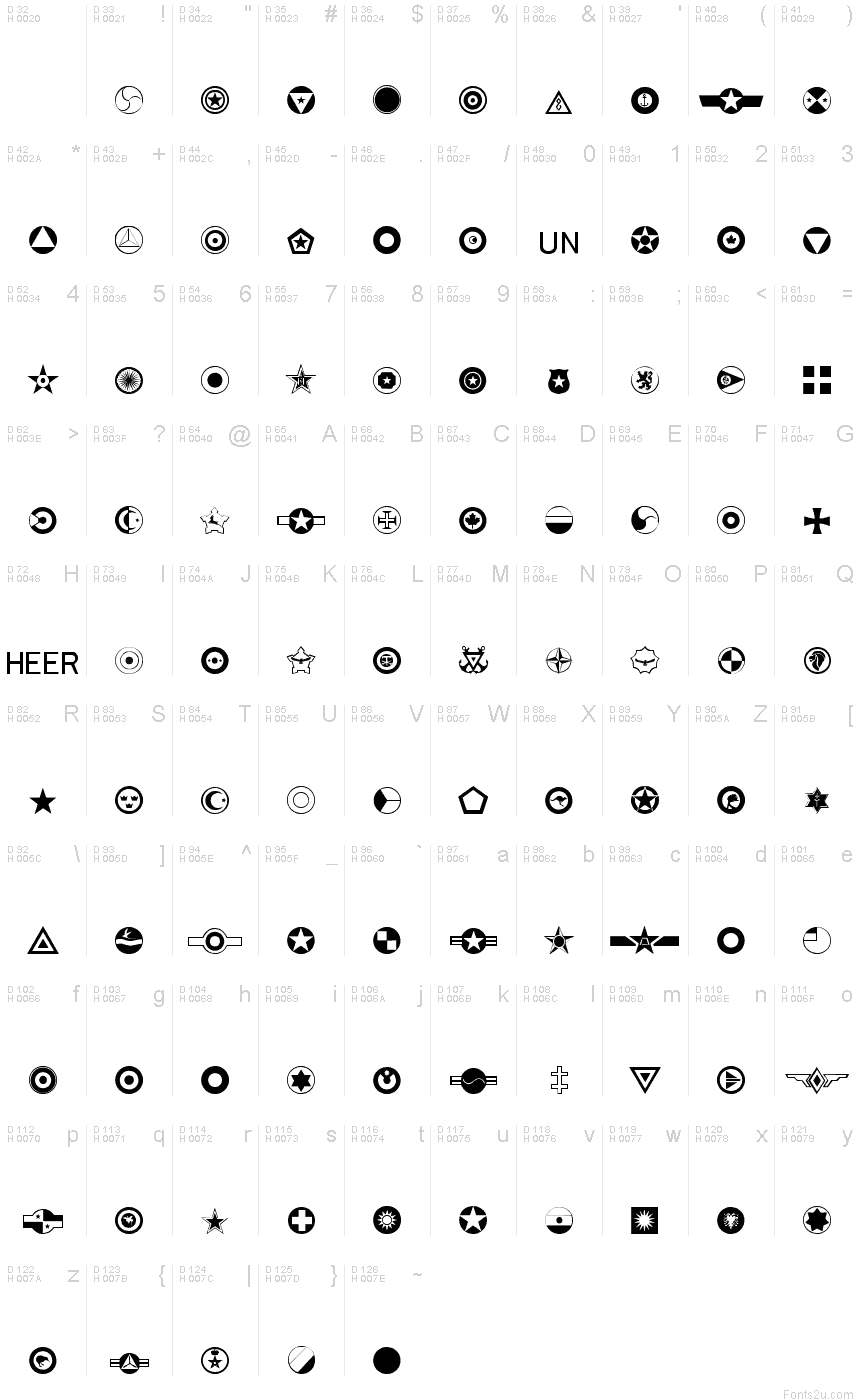
Roundels フォント
Iconian Fontsの「Roundels」は、大胆なエンブレムや記章、星を中心としたバッジをテーマにした無料のディングバットフォントです。はっきりとした円形や翼のモチーフ、鋭い幾何学模様が特徴で、航空機のマーキングや部隊章、簡略化された指揮官用標識のような、力強く無骨な雰囲気をアイコンに与えています。
ポスターの見出しやゲームのHUDグラフィック、車両用デカール、勢力のブランディング、タイトルカード、あるいは航空機やレトロな戦争のビジュアル言語を取り入れたパッケージなど、グラフィックシンボルでメッセージを伝えたい場面で、この無料フォントをぜひ活用してください。モチーフがコンパクトで左右対称、かつ説明的すぎずグラフィックとして完成されているため、特にエンブレムを強調するような短いデザインによく合います。